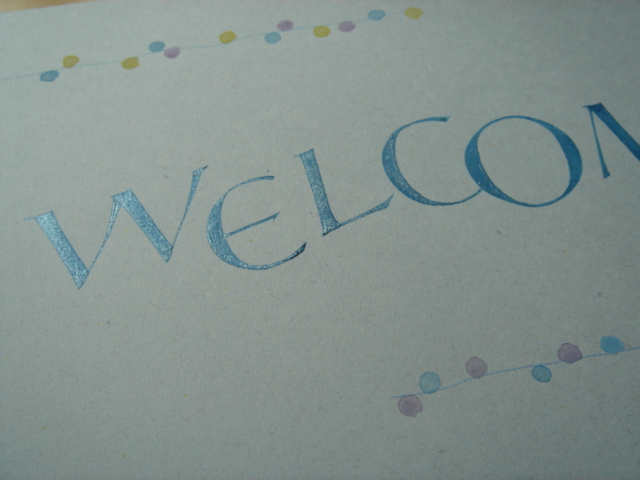
キラキラ!
先週、湿度100パーセント?と思えるくらい蒸し暑かった日に
カリグラフィーのカード講座があり、その入り口用に書いたWelcomeです。
パール色のメディウムを混ぜてキラキラさせてみました。
ちょっと塗りが厚ぼったくなってしまいましたが、色は涼しげだからひんやり感が出たような…気がする…
水玉模様は以前mojitor-hさんが紹介していた「1日10分で…」の吉沢深雪さんの水彩画ドリルのレッスンを実践!Winsor&Newtonから出ているIridescent Mediumです。
それで、この頃はカードを書くときなどに使って楽しんでいます。
絵の具に混ぜて使いますが、伸びがよくて、なめらか。ペン先からの絵の具の出具合も楽々です。